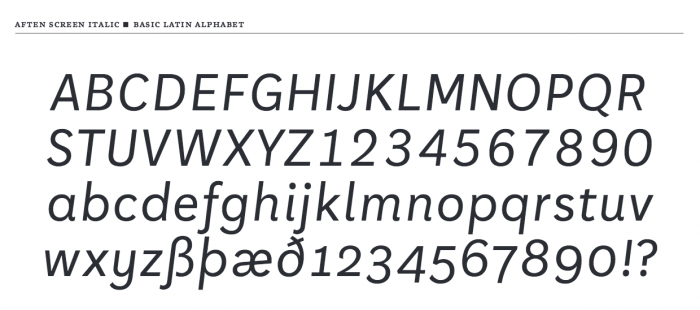
Freundlich aber neutrale Sans mit freundlicher Kursive
ich suche eine ruhige Serifenlose (Freundliche, dynamische Anmutung. Hier im Beispiel ›Alright Sans‹) mit einer Kursiven, die im Abstrich der Letter so einen kleinen Bogen macht wie die Aften Screen Italic (Screenshot).
Habt ihr da was im Hinterkopf?
Wie wäre es damit?:
Dynamisch:
• Auto 2 (Underware)
• Mr Eaves (Emigre)
• FF Milo
• FF Tisa Sans
Statisch:
• National (Klim)
• Guanabara Sans (Plau)
Geometrisch:
• Remo (Ourtype)
• Sharp Sans